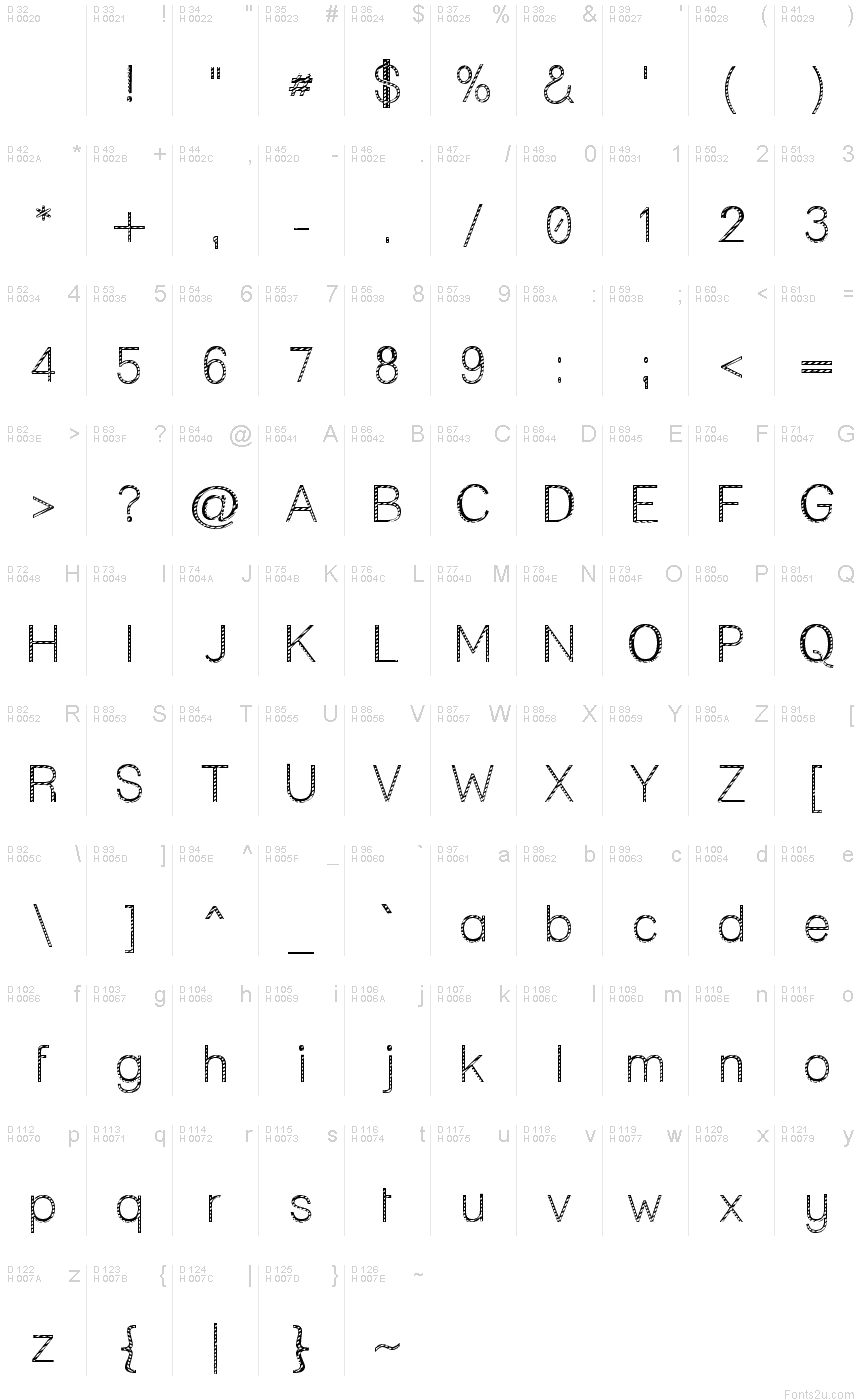
Lane - Cane autorstwa Grahama Meade’a to darmowy, dekoracyjny krój displayowy z wzorem pasków w stylu lasek cukrowych biegnącym przez każdą literę. Otwarte kontury i powtarzające się ukośne pasy nadają mu zabawny, wycinankowy charakter, który wyróżnia się na tle zwykłych fontów okolicznościowych.
Ten darmowy font świetnie sprawdza się na świątecznych opakowaniach, zaproszeniach, tytułach plakatów, w oznakowaniach i etykietach sezonowych, gdzie rytm pasków sam w sobie tworzy klimat. Lane - Cane pasuje również do brandingu rękodzieła, ulotek wydarzeń i świątecznych nagłówków – wzór pozostaje czytelny w dużych rozmiarach, dodając krótkim tekstom pogodnego, ręcznie wykonanego charakteru.
Lane - Cane
Graham Meade